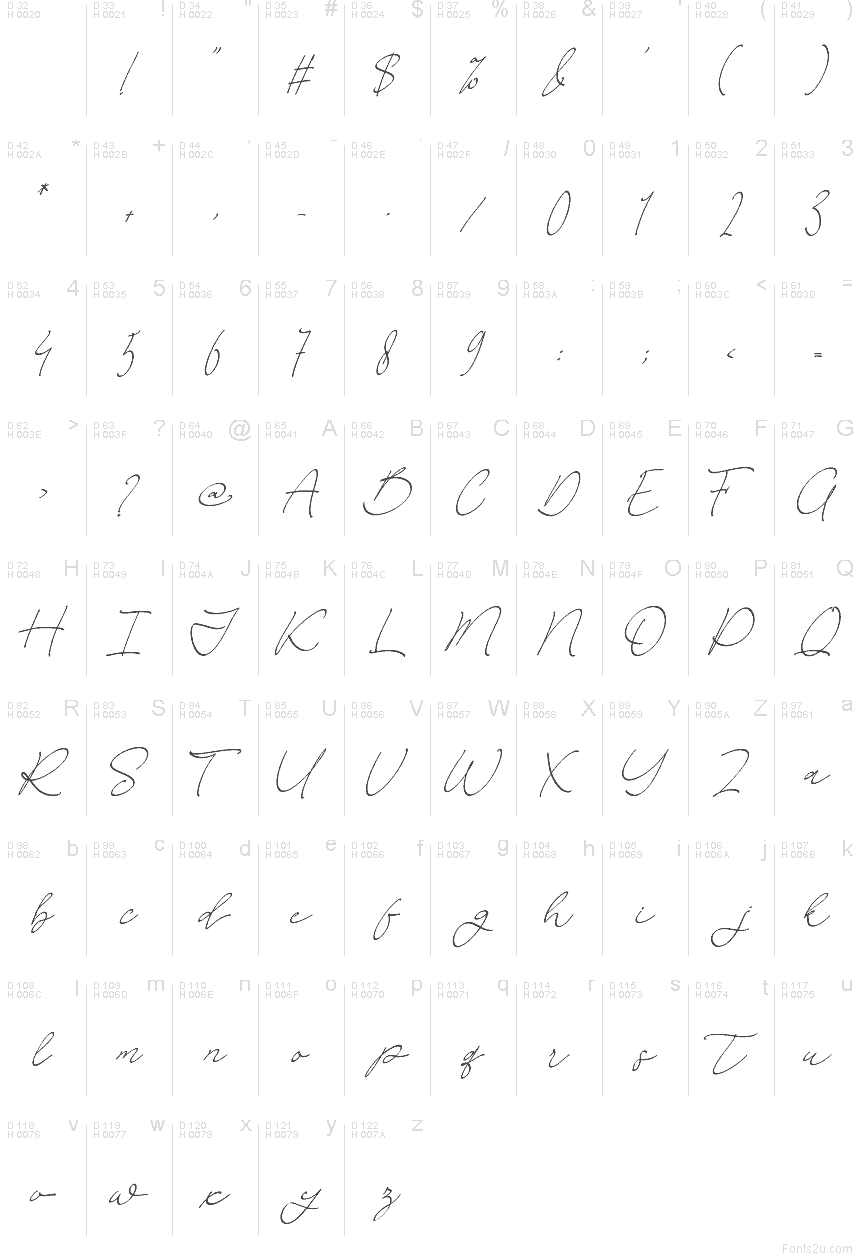
Baighan od Pineungtype je bezplatné rukopisné písmo, které definují dlouhé, vzdušné smyčky a lehký kurzivní rytmus, díky němuž působí písmo otevřeně a nezahuštěně. Vysoké tahy a protáhlé křivky mu dodávají elegantní švih, který působí osobitě, aniž by sklouzával k drsné textuře štětce.
Tato plynulá silueta se skvěle hodí na svatební oznámení, podpisová loga, obaly kosmetických produktů, citátové grafiky a nadpisy na sociálních sítích, kde jemná ručně psaná linka dokáže podpořit celkový vzhled. Krátká jména a stručné fráze obzvláště těží z velkorysých smyček, které vytvářejí dekorativní zakončení bez potřeby dalších ozdob kolem textu.